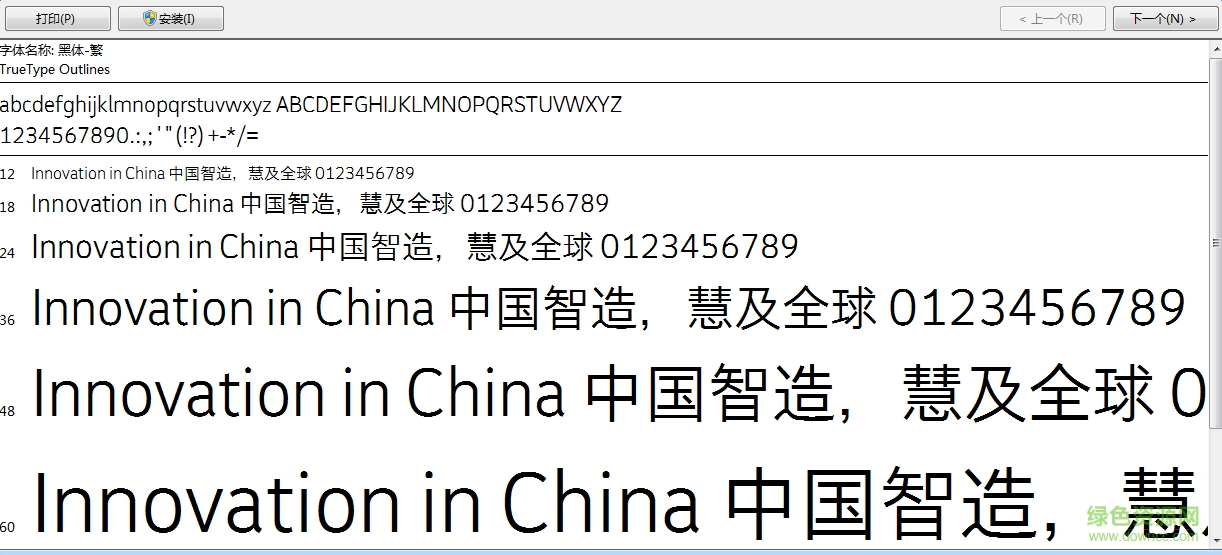
Heiti SC Medium字體是一款字形有沒的英文電腦字體,字體改編自華文黑體,具有非常鮮明的特點,十分適用與設計和PPT演講,有喜歡的朋友千萬不要錯過,歡迎來綠色資源網(wǎng)下載使用!
Heiti SC Medium 是一款來自華文黑體的英文字體,字體受傳統(tǒng)中國書法美學的影響,結構外弛內張,構成的字體感覺傳統(tǒng)儒雅,而且充滿人性,比起新派設計-負空間講究平均分布的,在以漢字為主的文字上可讀性要勝一籌。